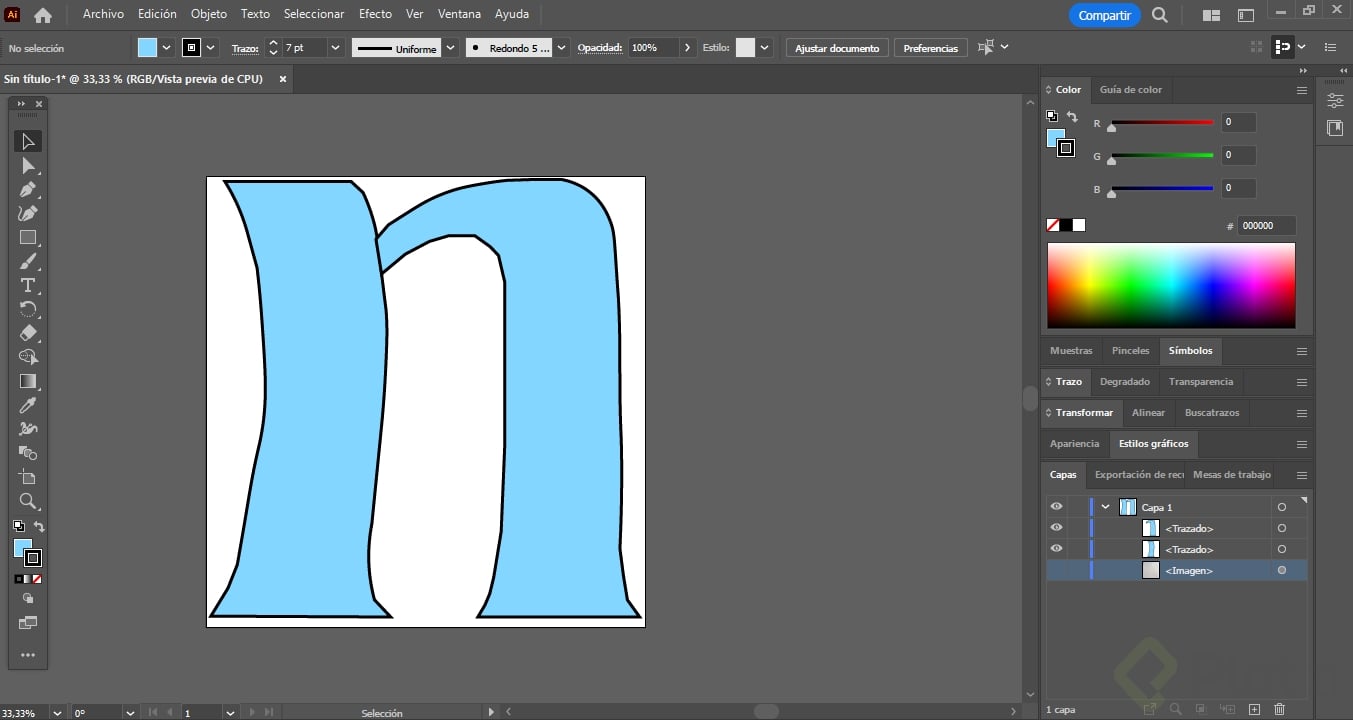
Domina la vectorización desde lo básico
Vectorizar puede ser sencillo si sigues un método claro y estructurado.
Trabajaremos pensando en los ejes X e Y y usando pasos prácticos que garantizan precisión y eficiencia.
Empezaremos con la letra "N", una elección estratégica por su versatilidad
El arte de vectorizar: comienza con la letra N
La "N" combina líneas rectas y curvas, permitiendo:
Reutilizar elementos: sus componentes pueden adaptarse para otras letras.
Simplificar la estructura: es un buen punto de partida para practicar proporciones.
Antes de comenzar:
Configura tu trabajo con estas características:
- Peso bold y ancho condensado en el tipo de letra.
- Serifas en forma de cuña.
- Altura de X moderada.
Definiendo los parámetros básicos
Ejes principales:
Eje Y: movimiento vertical.
Eje X: movimiento horizontal.
Ancho base: define un ancho de 600 unidades (valor por defecto). Ajusta según tus necesidades.
La estructura de la "N"
La "N" consta de dos trazos principales:
Trazo vertical izquierdo: un rectángulo simple, sin nodos adicionales.
Trazo curvo derecho: combina una curva y un trazo vertical.
Tip para replicar formas:
Usa la tecla Alt mientras arrastras para duplicar elementos.
Esto funciona en Glyphs e Illustrator.
Nodos: tipos y función
En Glyphs, los nodos son esenciales para controlar los manejadores.
Existen tres tipos principales:
Nodo de acoplamiento: mantiene los manejadores unidos.
Nodo desacoplado: permite ajustar manejadores de forma independiente.
Nodo de dirección: define la orientación del contorno.
Consejo:
Para evitar espacios en blanco indeseados, verifica que los nodos de dirección apunten hacia el mismo lado.
Usa la función "Invertir contornos" si es necesario.
¿Cómo crear serifas efectivas?
Las serifas deben ser coherentes con el diseño general. Sigue estos pasos:
Distribuye puntos de anclaje: define los extremos de la serifa.
Alinea los puntos inferiores: usa herramientas de alineación para mantener la consistencia.
Verifica con el diamante rosa: confirma la alineación vertical en la línea base.
Tip:
Refleja y copia serifas con atajos de teclado para ahorrar tiempo.
¿Cómo lograr curvas armoniosas?
Ajusta los manejadores sobre la rejilla con las teclas Ctrl y Alt.
Usa movimientos precisos para preservar la estética de la curvatura.
¿Cómo garantizar proporcionalidad?
Mide la anchura de los trazos.
Ajusta manejadores con Shift y las flechas del teclado.
Confía en las herramientas automáticas de Glyphs para mantener las proporciones al mover nodos.
Siguiendo estos pasos, vectorizarás de manera eficiente y ordenada, maximizando el potencial de tus diseños.
Practica con la "N" y explora cómo reutilizar sus componentes para otras letras del alfabeto.